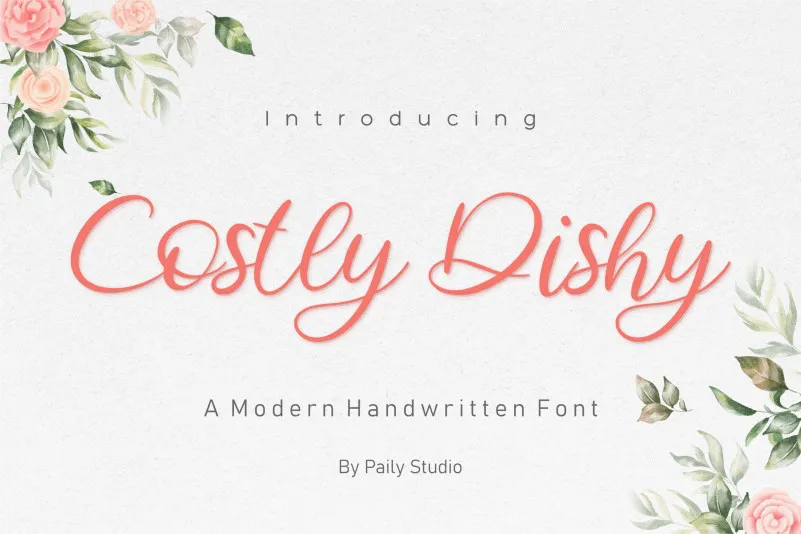
Costly Dishy Font – Download Grátis
Esta fonte moderna em estilo escrita a mão se destaca com sua aparência suave e versátil, perfeita para quem busca uma escrita autêntica que complementará qualquer projeto. Através de seu design delicado, o “Costly Dishy Font” se adapta para diversas aplicações, como projetos de casamento, criação de marca, logomarca, cartazes, cartões de nome, convites e postagens nas redes sociais. Seu estilo elegante é ideal tanto para uso pessoal quanto corporativo, permitindo que você personalize sua identidade visual sem sacrificar a fidelidade ou o toque autêntico do design. Ideal para quem busca expressar um pouco mais de emoção e personalidade em cada projeto, o “Costly Dishy Font” é uma fonte escrita a mão moderna perfeita para designers apaixonados pelo design gráfico.